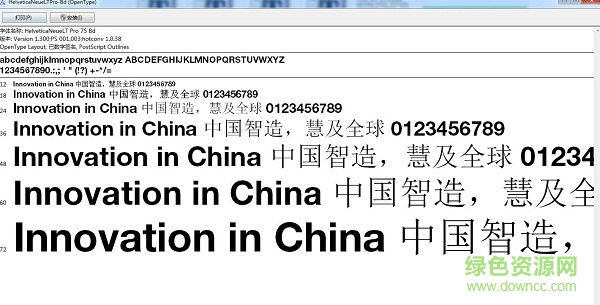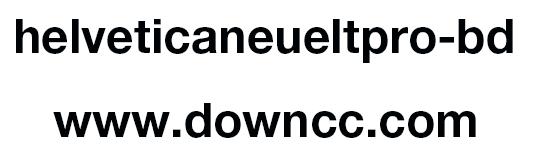
helveticaneueltpro-bd是什么字體?helveticaneueltpro-bd是一款百搭的經(jīng)典無襯線字體,字形簡潔規(guī)范,適用于促銷廣告、廣告海報等方面,喜歡的朋友快來下載吧!
無襯線字形比較方正,筆畫醒目并且粗細一致,簡單的理解就是沒有裝飾線的字體,無論是中英文都能傳遞直接干練的氣質(zhì)特點;
無襯線字體它的范圍也比較廣泛,可塑性很強!